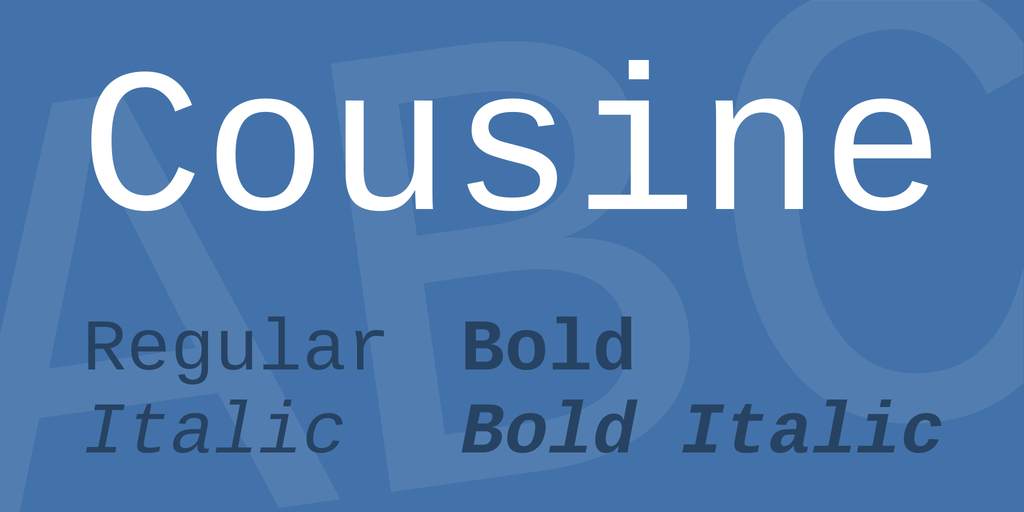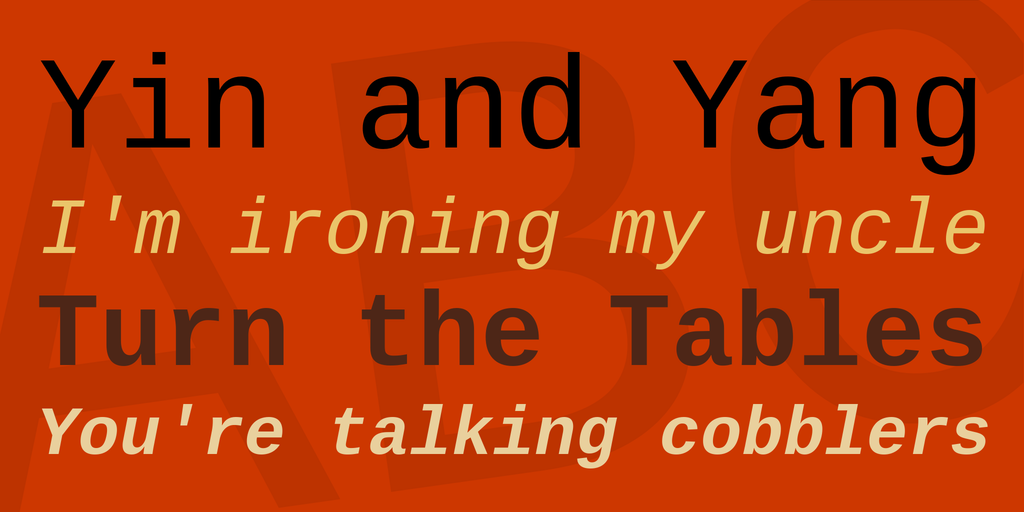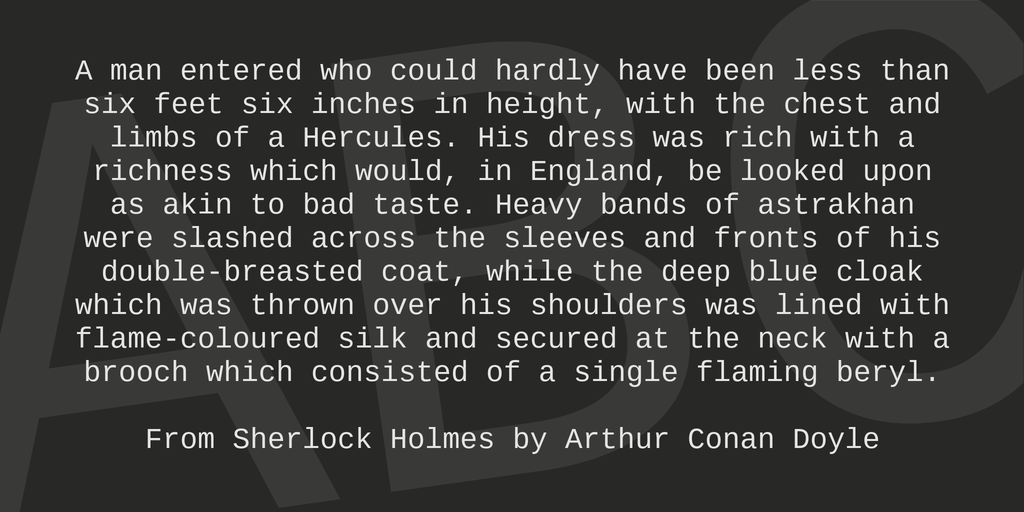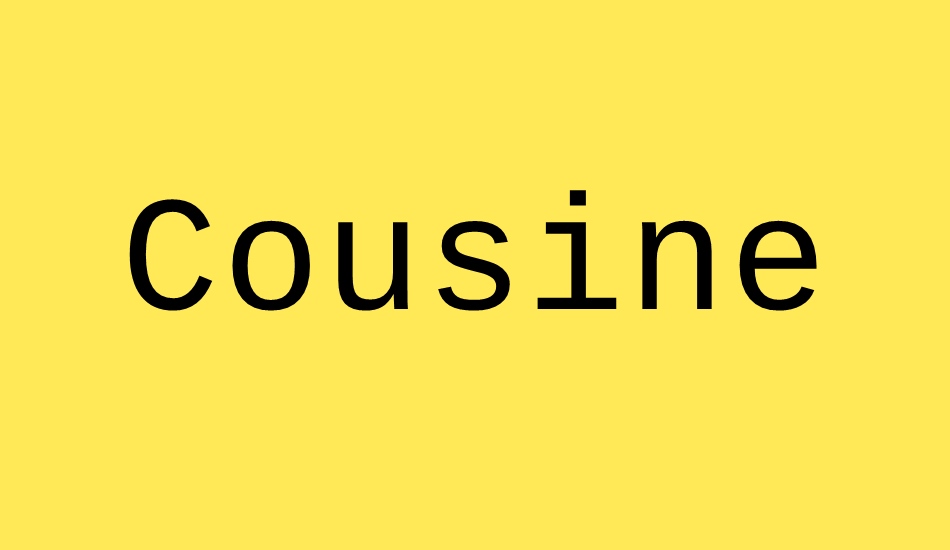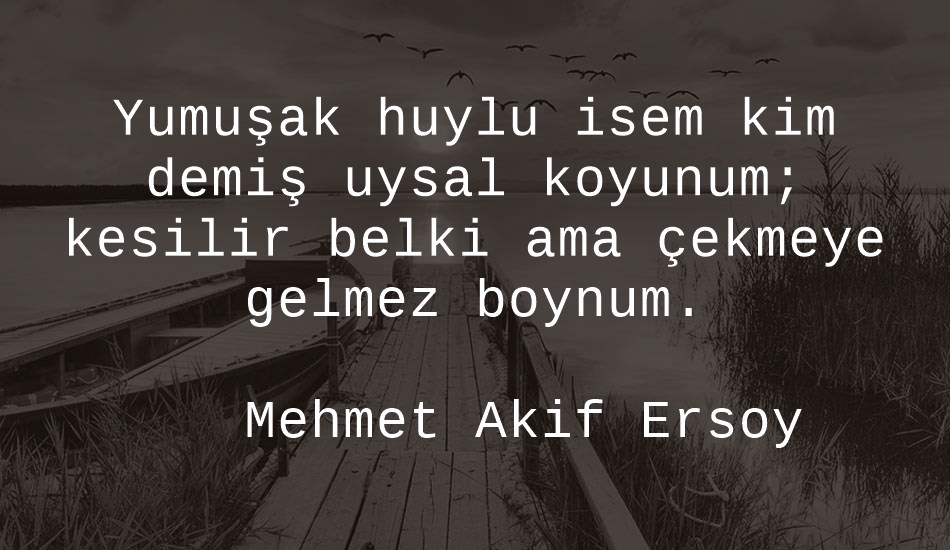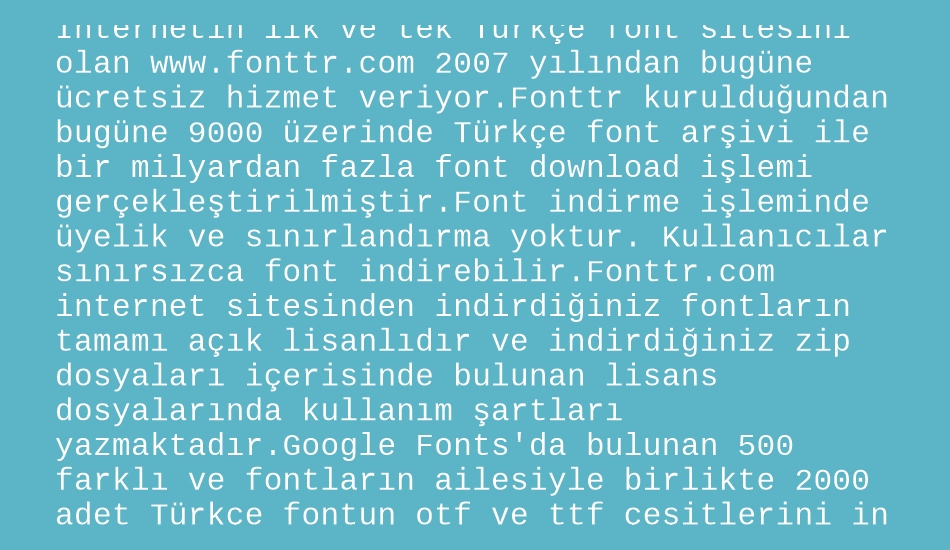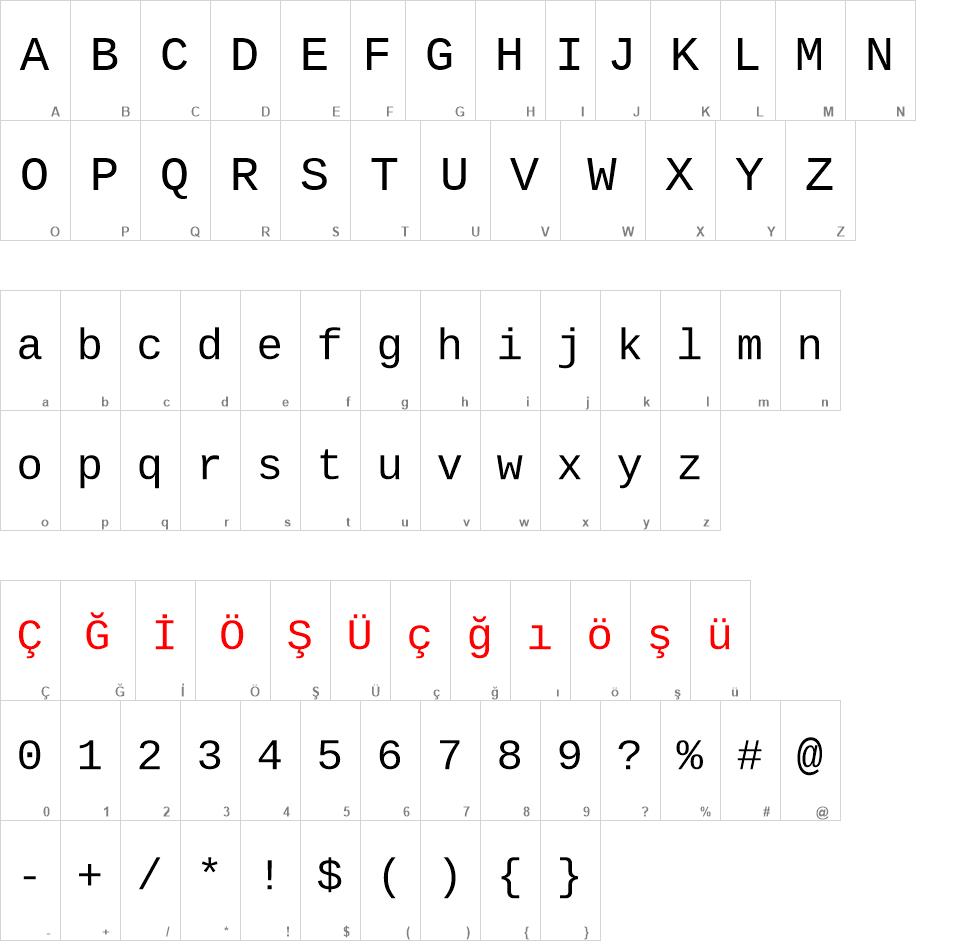
Cousine, Steve Matteson tarafından Courier New ™ ile metrik olarak uyumlu, yenilikçi, serinletici bir sans serif tasarımı olarak tasarlandı. Cousine font gelişmiş ekran okunabilirlik özellikleri ve Pan-European WGL karakter seti sunar ve platformlar arasında belge taşınabilirliğini ele alan genişlik uyumlu yazı tipleri arayan geliştiricilerin ihtiyaçlarını karşılar.
Cousine font